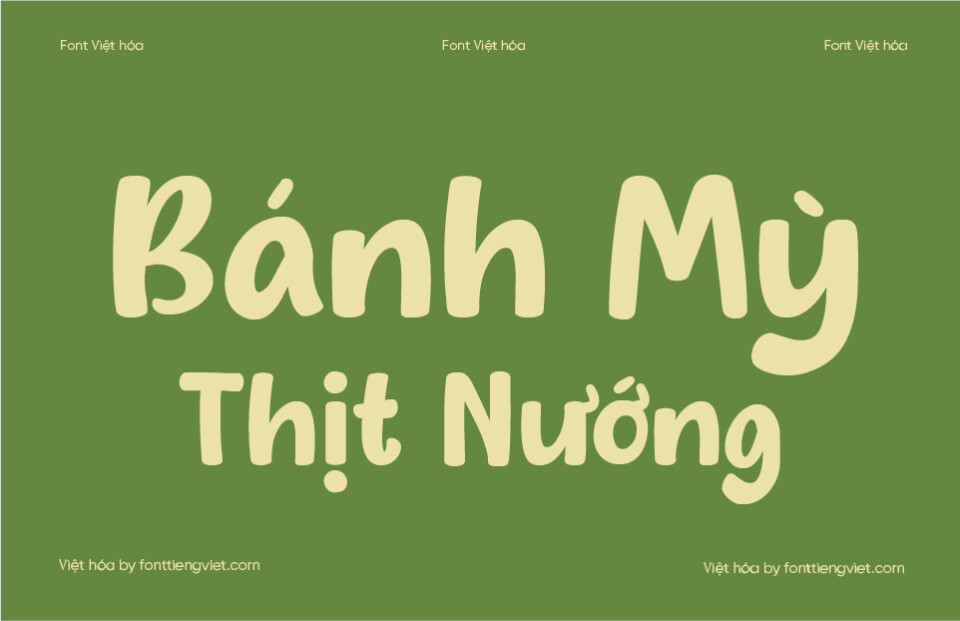
Font Việt hóa 1FTV VIP Season Prime
Trong thế giới đồ họa hiện đại, việc tìm kiếm một bộ chữ vừa mang tính thẩm mỹ cao vừa hỗ trợ đầy đủ tiếng Việt là điều vô cùng quan trọng. Font Việt hóa 1FTV VIP Season Prime nổi lên như một lựa chọn hàng đầu cho các nhà sáng tạo nội dung. Đây là bộ Font Miễn Phí được tinh chỉnh kỹ lưỡng để phù hợp với nhiều loại hình thiết kế từ đơn giản đến phức tạp. Với đường nét thanh thoát và hiện đại, bộ font này giúp các sản phẩm truyền thông trở nên chuyên nghiệp và bắt mắt hơn bao giờ hết.
Ưu điểm vượt trội của Font Việt hóa 1FTV VIP Season Prime trong học tập
Tính ứng dụng cao trong giảng dạy và trình bày
Font Việt hóa 1FTV VIP Season Prime sở hữu cấu trúc ký tự rõ ràng, giúp học sinh và giáo viên dễ dàng đọc hiểu nội dung trên các slide thuyết trình hoặc tài liệu học tập. Sự kết hợp giữa phong cách cổ điển và hơi hướng đương đại làm cho bộ font này không bị lỗi mốt theo thời gian. Ngoài ra, tính năng việt hóa chuẩn xác giúp loại bỏ hoàn toàn các lỗi hiển thị dấu câu thường gặp, đảm bảo văn bản luôn nhất quán và đẹp mắt.
Phù hợp cho nhiều dự án sáng tạo của học sinh
Không chỉ dùng trong văn bản hành chính, bộ font này còn là công cụ đắc lực cho các câu lạc bộ trường học khi thiết kế poster, tờ rơi hoặc áo lớp. Khả năng tùy biến linh hoạt của nó cho phép người dùng sáng tạo không giới hạn, tạo nên dấu ấn riêng biệt cho từng dự án cá nhân.
Kết luận về bộ font đẳng cấp này